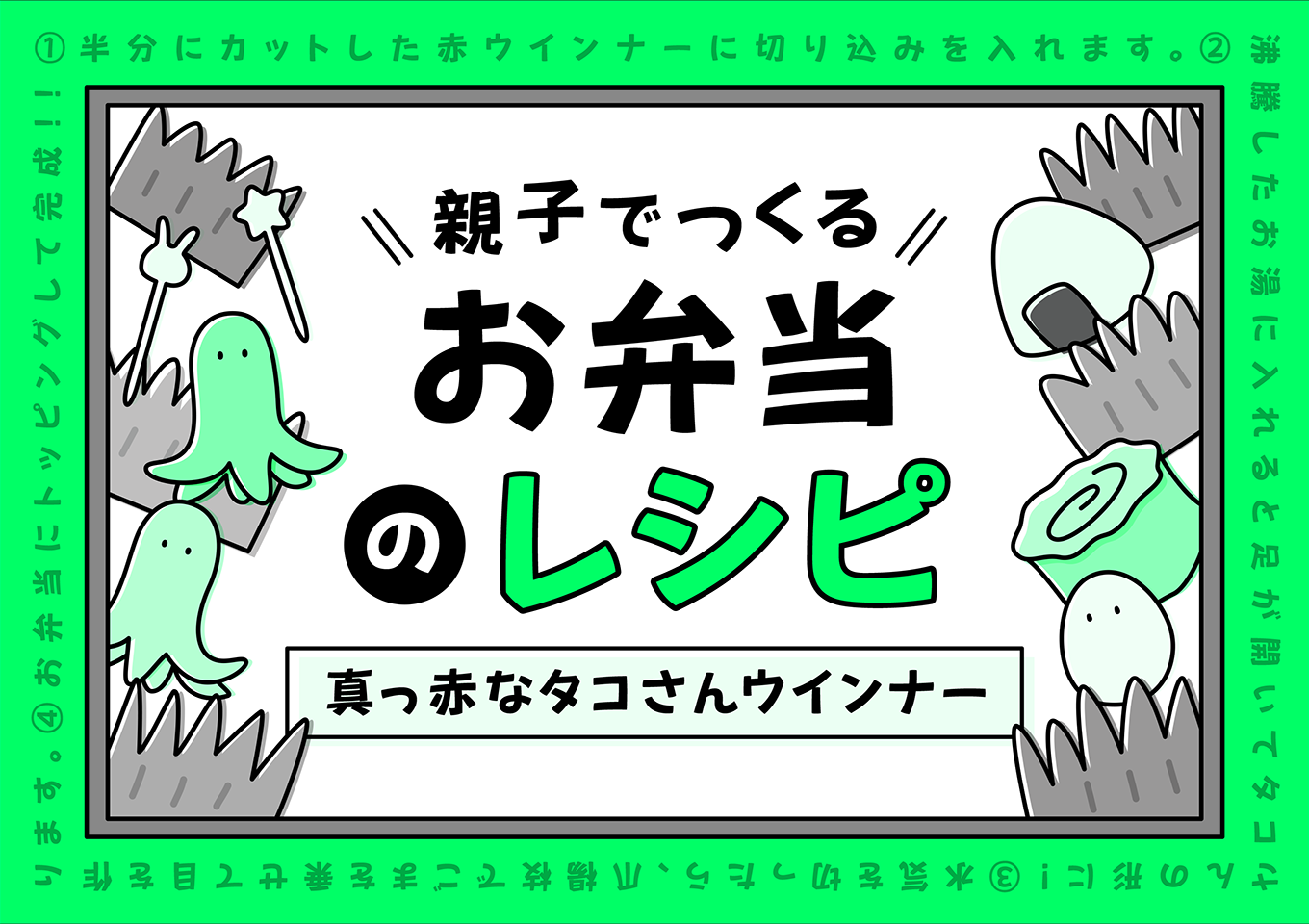
「翠流ゆゆポップ」は、太い平芯のマーカーペンで書いたような、親しみやすく楽しげな雰囲気を持つPOP体です。適度にアンバランスな文字のプロポーションが楽しさやホッとするような優しさを感じさせ、絵本やテロップ・POPなどの幅広い場面でお使いいただけます。なお、本書体はモリサワで制作したかな・英数字に、Arphic Typesの「AR悠々ゴシック体EB」の漢字を組み合わせています。